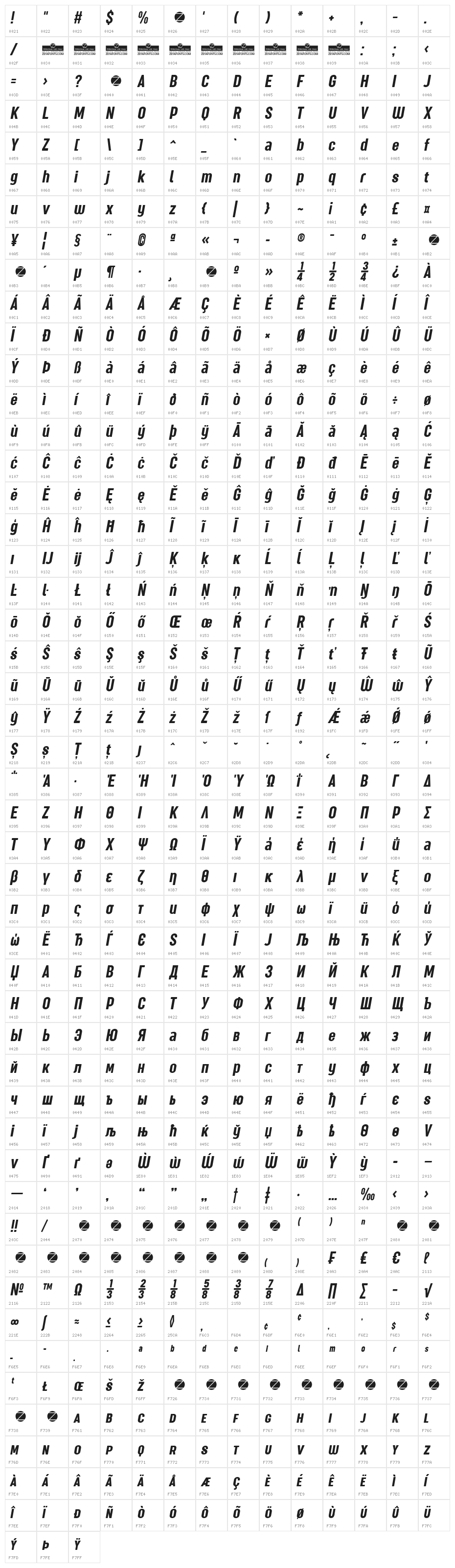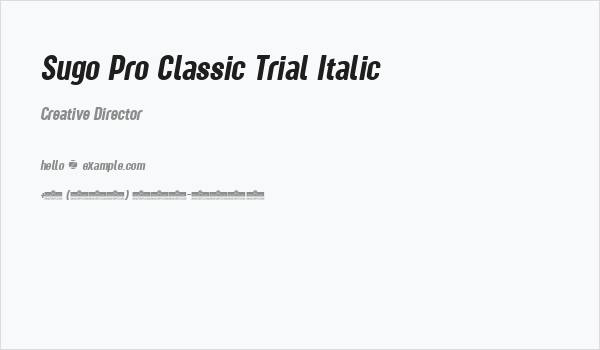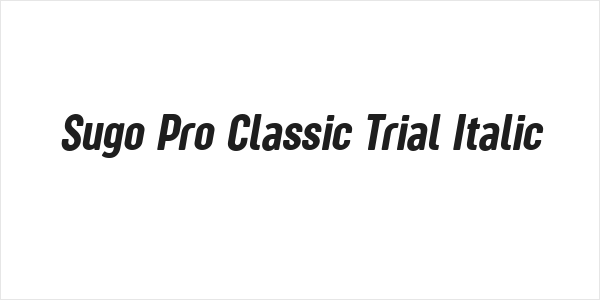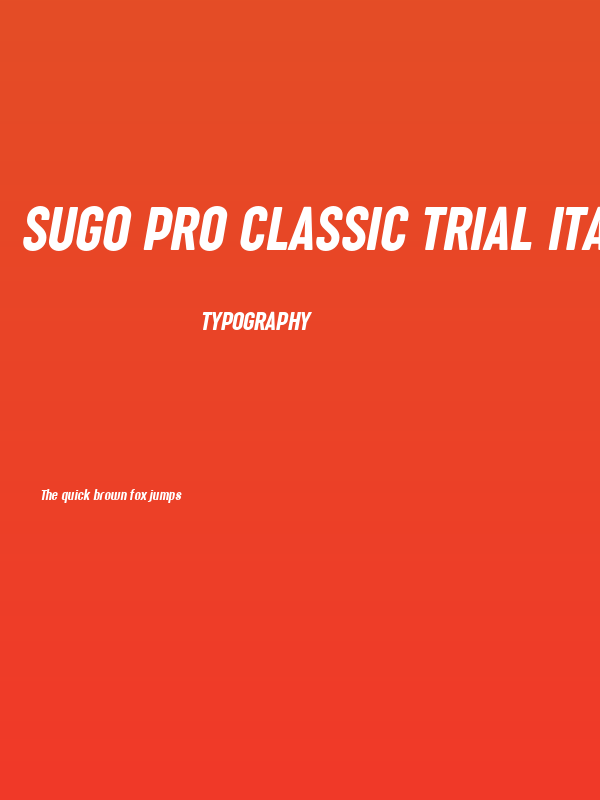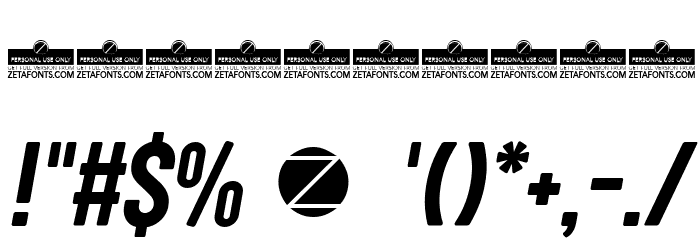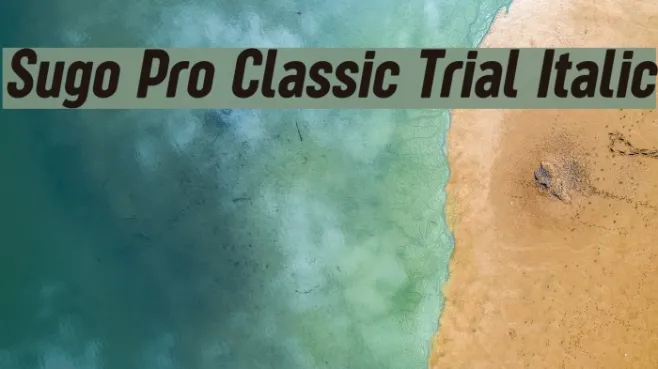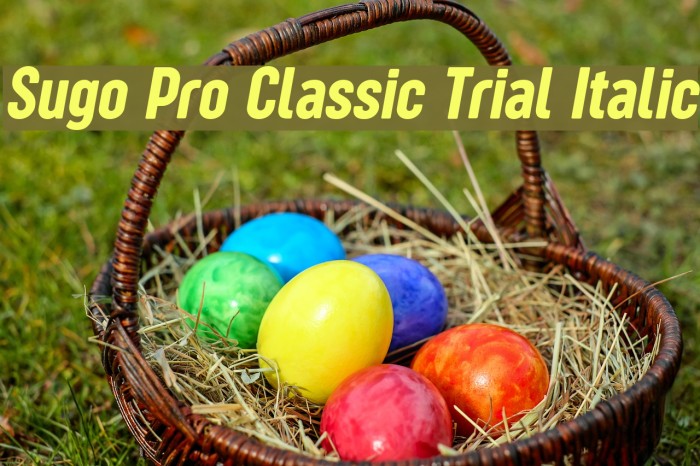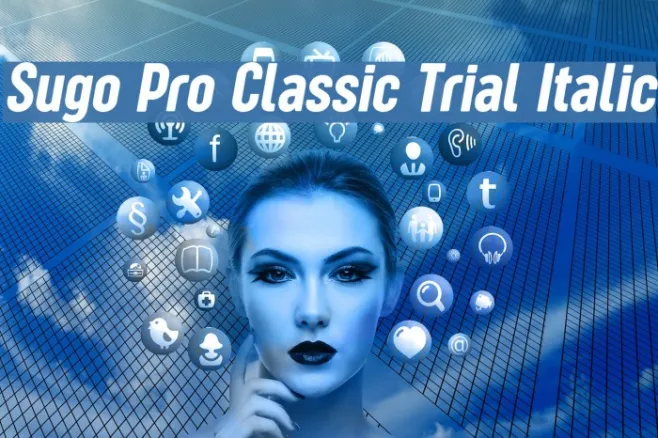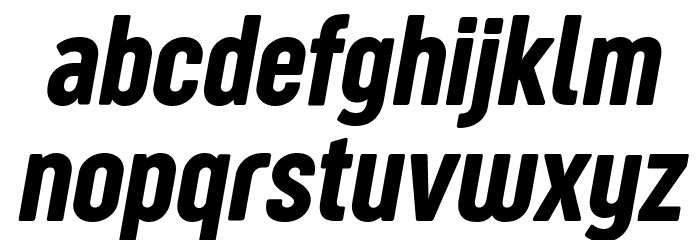
Sugo Pro Classic Trial Italic Font
| Caso de uso | Headlines, Logos, Branding |
| Proyectos propuestos | Ideal for branding, advertising, and headlines where a strong, modern presence is desired. |